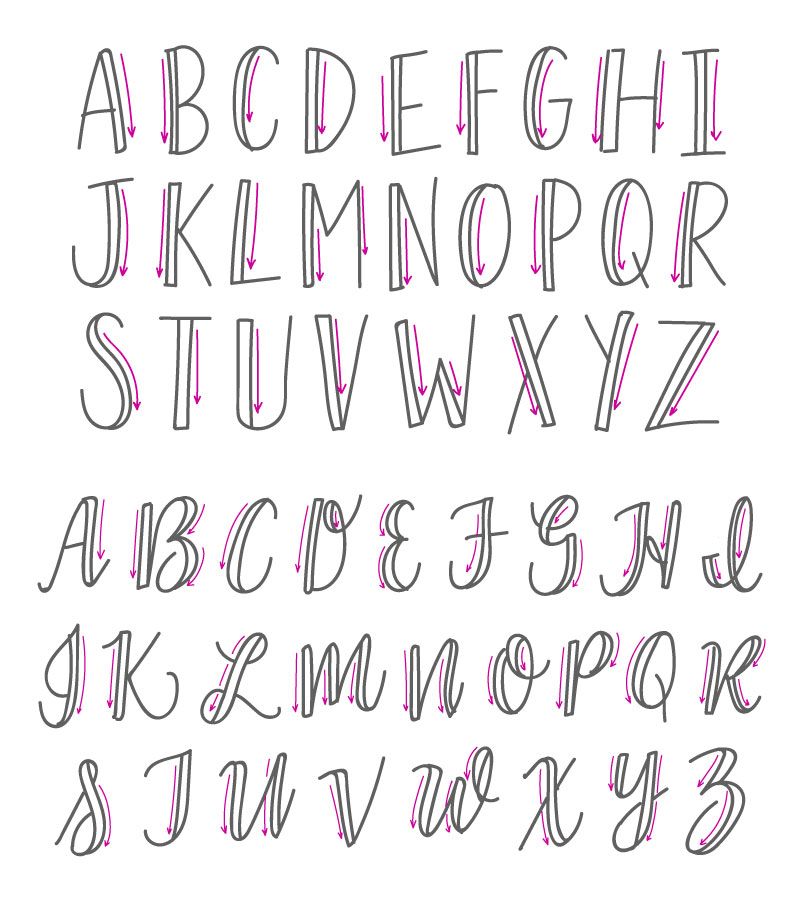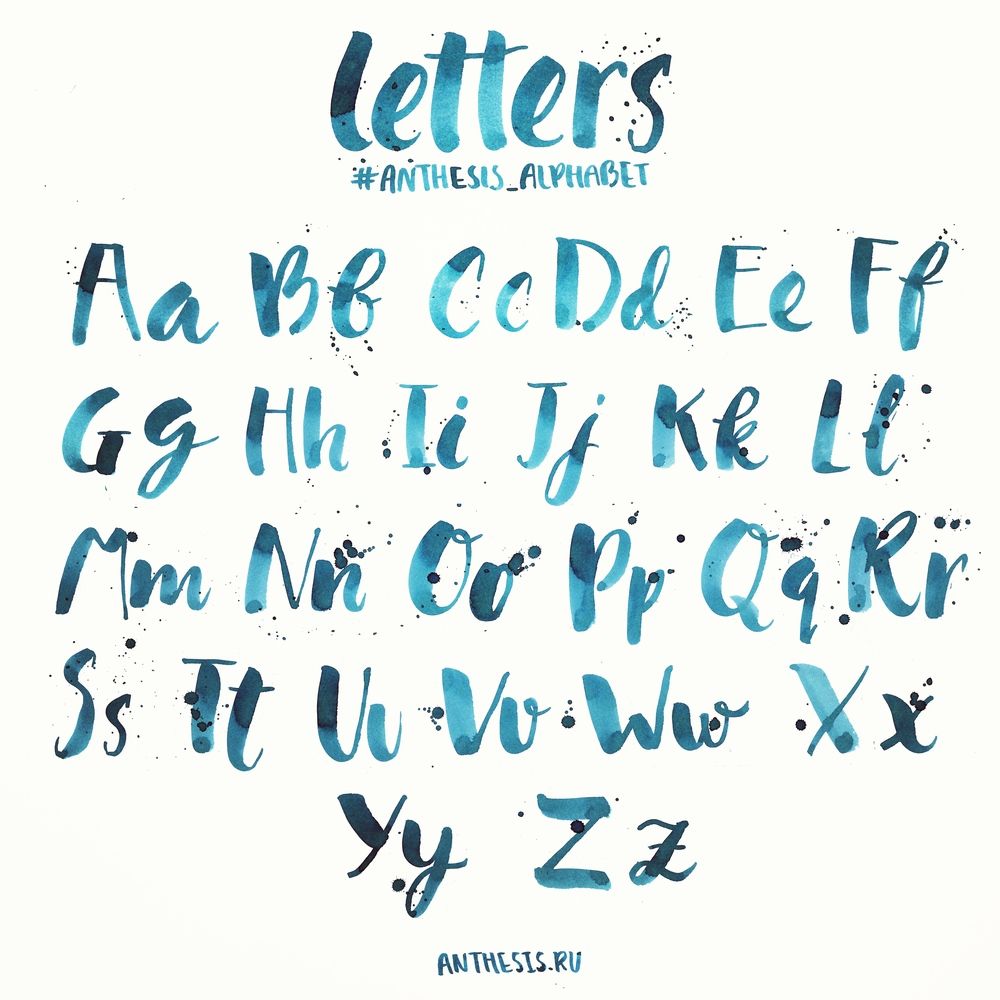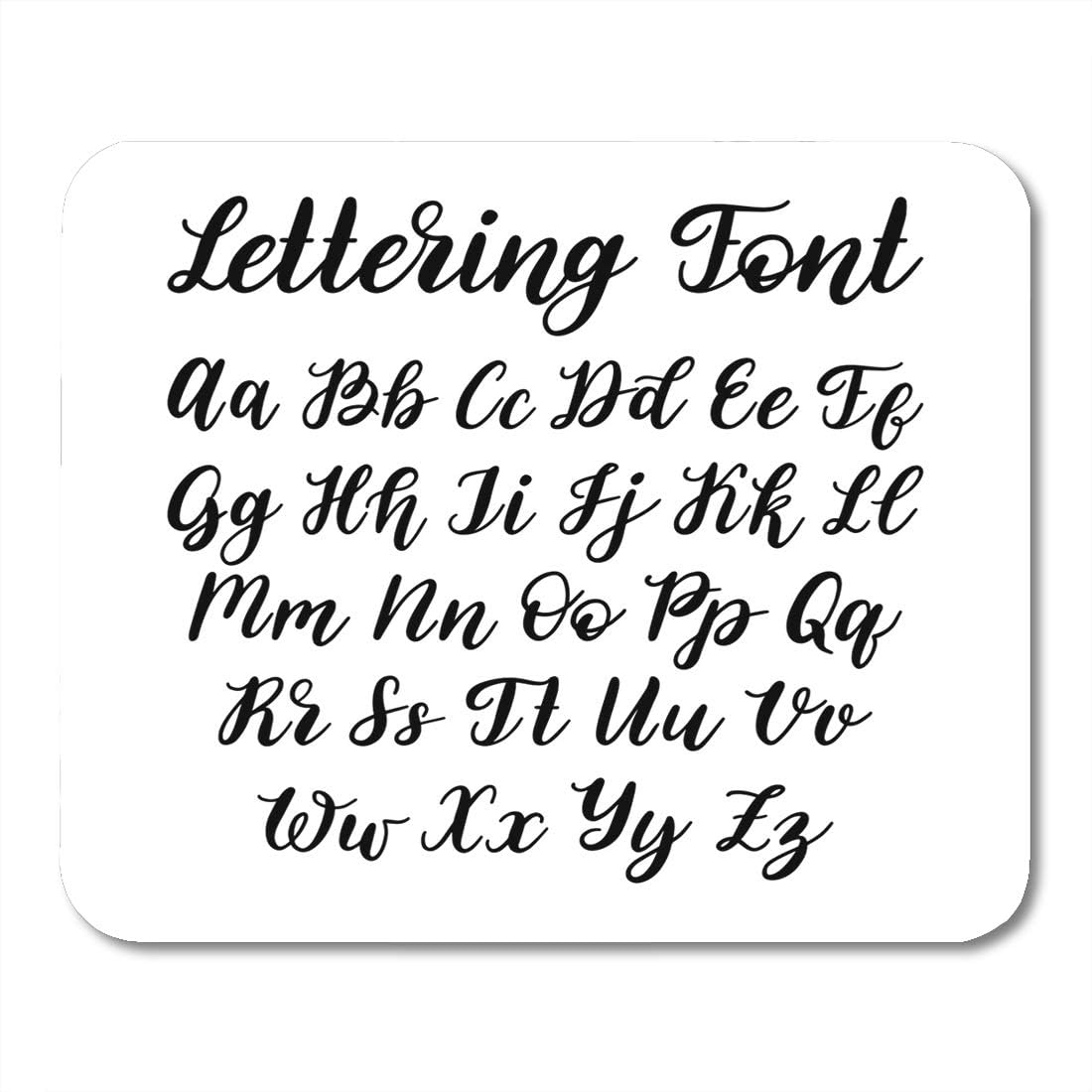
Леттеринг — отличный способ «одушевить» ваш проект
Большая обзорная статья от дизайнера Александра Кочеванова, который подробно рассмотрел отличия шрифта, леттеринга и каллиграфии, а также способы и особенности применения каждого в проекте.
Смотря фильмы про будущее мы очень часто видим такую картину: одинаковые, словно клонированные, люди в одинаковой одежде. Их окружают одинаковые автомобили и дома на одинаковых улицах. Люди трудятся на благо огромных корпораций, осуществляя монотонные телодвижения перед компьютерами или перекладывая бумажки с места на место.
Все вокруг бездушное и унылое, преобладают голубые, серые и белые оттенки с небольшими вставками ярких цветов для ключевых героев фильма. Наверняка это сделано для придания большей ироничности сюжету фильма. И, конечно, я отдаю себе отчет в том, что это утопия и в обозримом будущем такого не случится. Но одно я знаю точно. Я и подавляющее большинство людей никогда бы не захотели жить в таком мире.
Но некоторые отголоски такой картины можно наблюдать и сегодня. При решении многих задач мы используем шаблоны: фреймворки, конструкторы, шаблонные сайты, интерфейсы, логотипы, предметы быта и прочее. Все направлено на удешевление производства и быстрый выход на рынок. Выгода с экономической точки зрения, конечно, очевидна. Но со стороны потребителя становится скучно и однообразно.
Существует много способов «одушевить» продукт: придумать зверюшку-символ, использовать образы людей, фотографии, иллюстрации. Я расскажу вам о леттеринге. Осторожно — много картинок!
В первую очередь, нужно различать 3 понятия.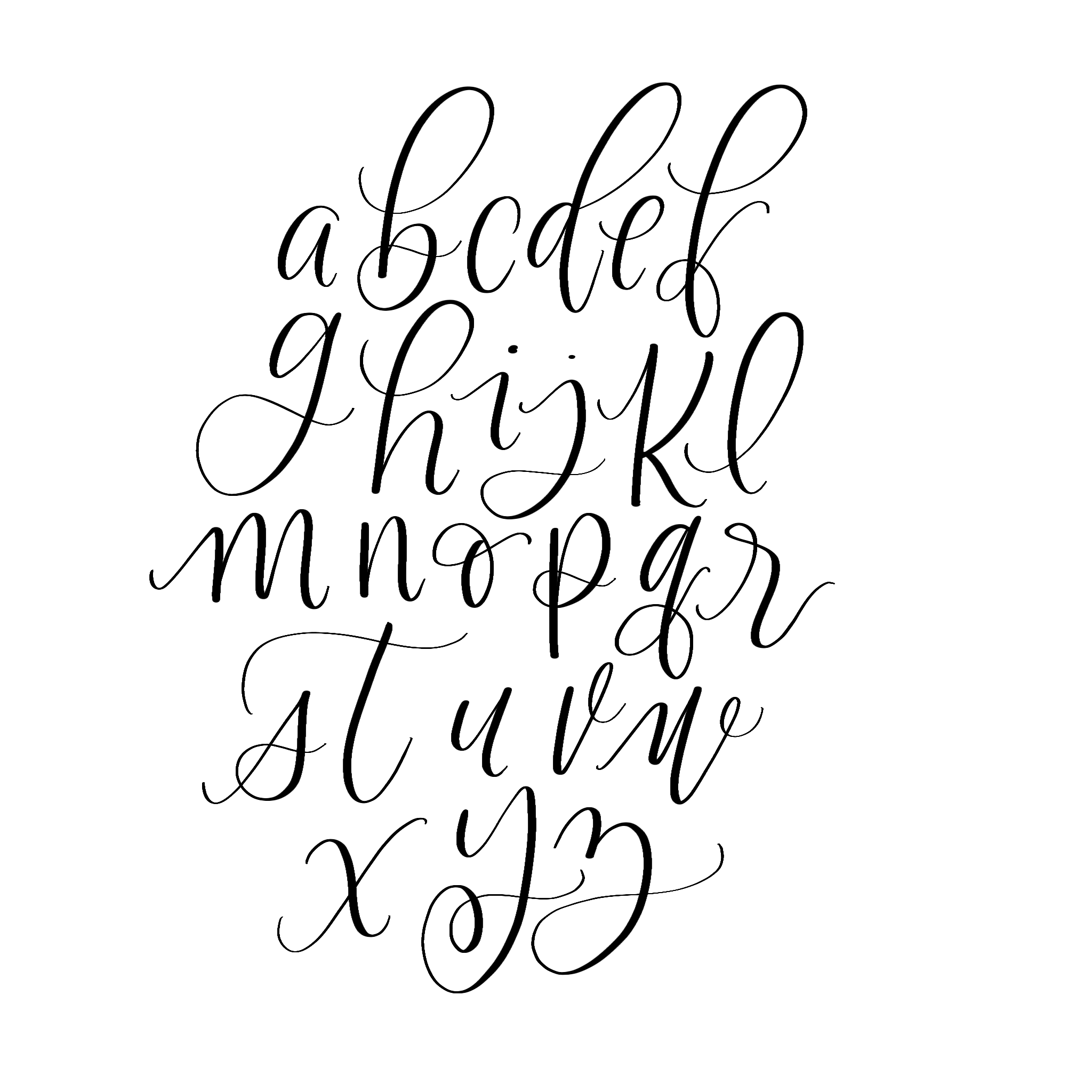
Шрифт — набор из символов, которые могут использоваться в любом порядке и служат для написания слов, предложений и текстов большого объема.
Леттеринг — уникальное рисование слова или словосочетания, изредка целых фраз, которое составляет единую композицию и предназначенное для конкретной ситуации.
Каллиграфия (с греческого «красивый почерк») это тоже ручная надпись, но, в отличие от леттеринга, все буквы должны придерживаться единого стиля и образовывать читабельный блок текста. Каллиграфией можно писать большие тексты, например грамоты или письма.
И леттеринг и каллиграфия создаются долгим и кропотливым трудом мастера. Но только леттеринг основан на вырисовывании букв и поиске уникального неповторимого сочетания символов, в то время как каллиграфия — это огромное количество повторений одних и тех же букв с целью написания текста в едином стиле.
Немного истории
Сначала были наскальные рисунки, в Древнем Египте были различные символы, потом появились буквы и цифры — человечество научилось писать.
Ручное письмо было повсюду: личные письма, книги, приказы и законы. Все писалось с помощью перьев: так зародилась каллиграфия. С появлением печатных машин и, вслед за ними, компьютеров начали появляться шрифты. Это очень способствовало повышению уровня образования. Книги стали более доступны, даже простые крестьяне и рабочие, со временем, научились читать и писать. Тем временем, леттеринг с появлением письменности развивался постоянно. Нужно было как-то оформлять вывески, афиши, этикетки, обложки.
Приятная тенденция
Я считаю, что сегодня, если и не пик, то рост использования леттеринга точно. Сегодня многие компании стараются сделать свои бренды «живыми». Появляются не магазины и бутики, а лавки: творческие, мясные, булочные, швейные и прочие. Это, в некоторой степени, возврат к прошлому. Оформляются логотипы таких заведений именно леттерингом. Внутри очень часто можно встретить меловые стены с меню или просто с изображением продукции.
Потому что, это создает атмосферу тепла и уюта. И мне это нравится.
Ровно год назад в новогодние дни на первом канале транслировались крутые вставки созданные с помощью доски и мела.
Процесс создания можно посмотреть на сайте Игоря Мустаева. Очень интересно.
Мировые СМИ и такие печатные издания как Time, Esquire, Vogue, Forbes по полной используют этот инструмент.
Огромное количество логотипов создано с помощью леттеринга. Конечно, Вы можете сказать, что их намного меньше чем классических логотипов, набранных каким-нибудь шрифтом. И вы будете абсолютно правы. Многие хотят выглядеть серьезно и в некоторых случаях это даже необходимо. Но очень многому количеству компаний был бы к месту именно «ручной» логотип.
И не подумайте, что я призываю все бросить и везде подряд использовать рисованные буквы. Я просто прошу обратить на это внимание, как на прием воздействия на потребителя. Но если, все-таки леттеринг вам интересен, листайте дальше.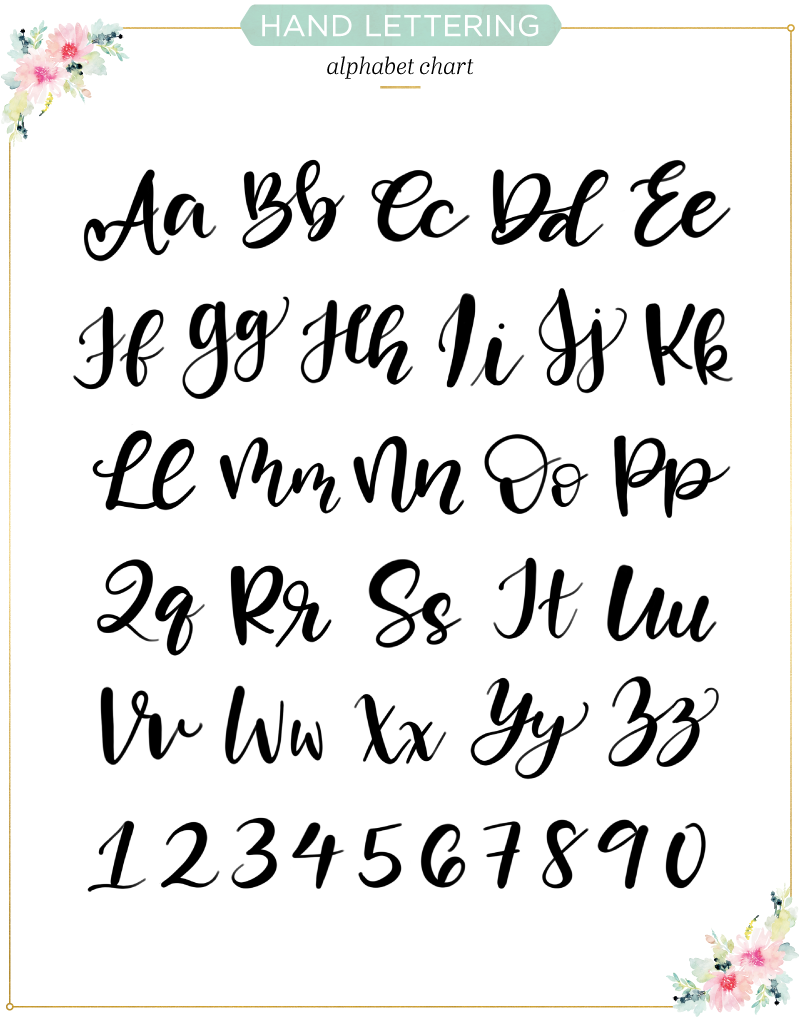
Кто поможет с леттерингом?
Некоторое время назад, заинтересовавшись леттерингом, мне потребовалось место, где бы я мог складировать все найденное интересное. Я кидал все в этот паблик.
Мне попадалось много “забугорных” мастеров, но я решил сконцентрироваться на русскоязычных каллиграфах, леттерерах, дизайнерах и иллюстраторах. Находятся они, в большинстве своем, в России и на постсоветском пространстве. Попадались люди разной квалификации. Ниже я приведу список всех 226 человек. Но в первую очередь 30 тех, кто на мой взгляд круче.
Очевидно, кто-то мог не попасться мне на глаза, если есть дополнения, смело пишите в комментах.
1. Александр Стэн
2. Андрей Мартынов
3. Андрей Хобб
4. Виктор Пушкарёв
5. Виктор Севрюков
6. Виктория и Виталина Лопухины
7. Владимир Егошин
8. Гоша Бондарев
9. Даша Левчук
10. Дмитрий Ткачёв
11. Евгения Пестова
12.
Иван TAKNADO Fans
13. Игорь Ветошкин
14. Игорь Мустаев
15. Катерина Рахманова
16. Кирилл Плотников
17. Макс Брис
18. Мария Скопина
19. Михаил Левченко
20. Миша Новожилов
21. Назим Исмагилов
22. Никита Райзвих
23. Ольга Васик
24. Родион Илюхин
25. Сергей Шапиро
26. Стас Курап
27. Эрик Мусин
28. Юлия Тасито
29. Evgeny Tkhorzhevsky
30. Kirill Richert Mihailovich
Есть еще один мастер, которого я сначала вообще не хотел включать в этот список, но потом решил упомянуть. Потому, что его работы, как правило, носят декоративный характер, и не имеют практического применения. Его работы — это искусство, смотря на которые можно только получать эстетическое удовольствие. Речь идет о Покрасе Лампасе.
Источник: habrahabr.ru
- #каллиграфия
- #леттеринг
- #типографика
- 0
10 алфавитов для написания букв от руки, с которыми вам нужно попрактиковаться Прочитайте мое раскрытие здесь.
10 Рукописные листы по написанию алфавитов. Используйте эти рабочие листы с вашим Tombow Fudenosuke и разработайте свой собственный уникальный стиль письма!
Хотите улучшить свой почерк или придать ему художественный вкус? Эти бесплатные рабочие листы для практики письма от руки помогут вам научиться рисовать буквы, практиковать штрихи и создавать алфавит.
Один из лучших способов попрактиковаться в написании букв и выработать свой собственный уникальный стиль — использовать разные шрифты.
Практикуя разные способы рисования одной и той же буквы, вы начнете замечать, какие стили вам нравятся, и, прежде чем вы это узнаете, вы начнете видеть, как ваш собственный стиль воплощается в жизнь.
Прокрутите вниз, чтобы найти 10 алфавитов, написанных от руки, и почему бы не делать по одному алфавиту в день в течение 10 дней!?
Рабочие листы с алфавитом от руки всегда популярны, и эти рабочие листы охватывают как прописные, так и строчные буквы алфавита.
Со всеми этими практическими таблицами вы научитесь писать письма в кратчайшие сроки.
Помните, практика — единственный способ добиться совершенства. Поэтому убедитесь, что каждый день немного тренируетесь писать от руки.
Как начать писать?
Интернет полон написанных от руки цитат и изображений, которые могут вас вдохновить. Вы можете найти вдохновение в Instagram, выполнив поиск #handletred и прокрутив ленту вниз (часами, если вы чем-то похожи на меня!) или проверить Pinterest и создать новую доску для вдохновения от руки.
Когда вам надоест прокручивать ленту, вы можете начать изучать стили, которые вам нравятся, и отмечать, что вам не нравится.
Когда вы будете готовы попробовать написать надпись, все, что вам нужно, это обычный карандаш или какой-либо маркер (маркер Crayola отлично подойдет) и лист бумаги!
Правильные расходные материалы облегчат написание рукописных букв, но вам не нужно сразу же идти и тратить целое состояние на ручки и карандаши или насадки для кистей.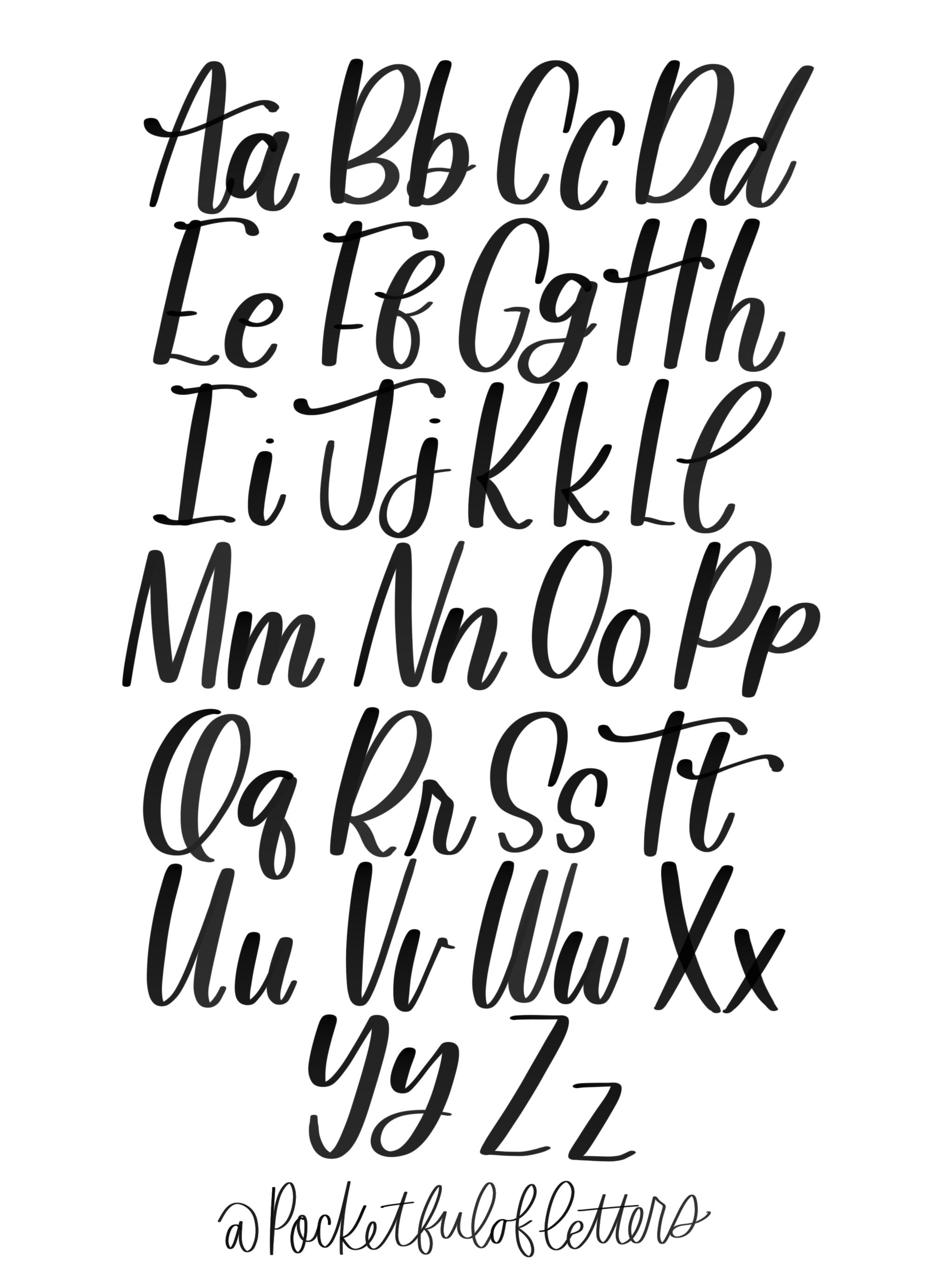
Возьмите маленькое слово или просто букву по вашему выбору и нарисуйте ее всеми возможными способами. Заполните хотя бы целую страницу разными вариантами буквы или слова.
Просто начните играть с буквами и получайте удовольствие. Не беспокойтесь о том, что это хорошо или красиво, потому что нет ничего неправильного или правильного, когда дело доходит до надписей. Это просто о том, чтобы попробовать что-то новое и посмотреть, как далеко вы можете продвинуть свои буквы, и это делает это таким увлекательным!
Как научиться писать от руки?
Есть много книг и видео, которые помогут вам научиться писать от руки, но вы не научитесь, пока не начнете прикладывать ручку к бумаге.
Перед тем, как вы погрузитесь в буквенное обозначение, важно знать наиболее часто используемые термины, чтобы в следующий раз вы могли называть «маленькую штучку на конце строчной буквы» ее именем — терминалом. . Зная эти термины, вы сможете говорить с кем угодно на эту тему.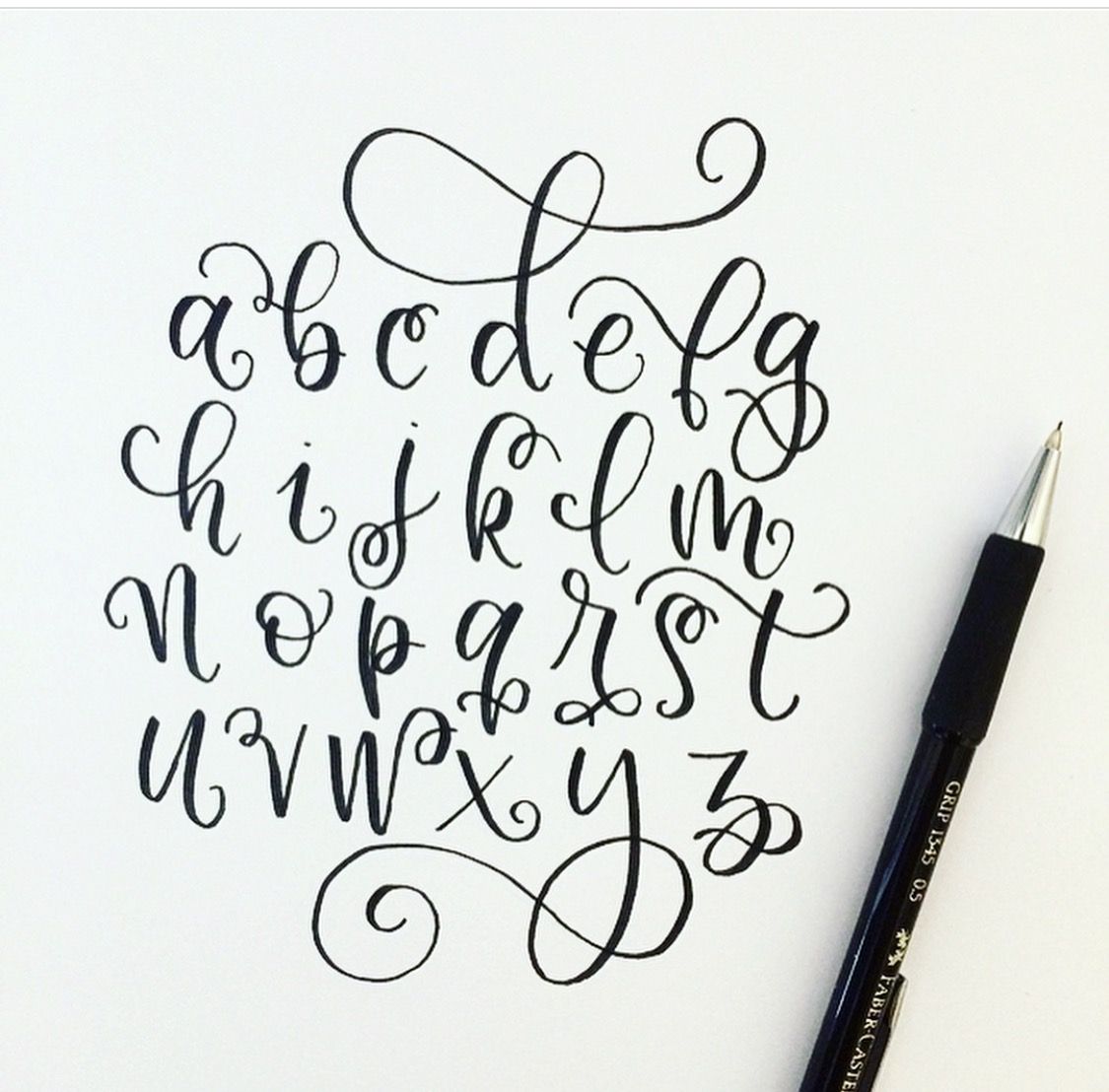
Какие ручки лучше всего подходят для письма от руки?
Чтобы начать рисовать от руки, вам не нужны какие-то причудливые и дорогие ручки-кисти. Если у вас дома есть пара маркеров Crayola, все готово! У маркера Crayola нет наконечника-кисти, но он по-прежнему остается одной из самых популярных ручек для надписей.
Если вы все же хотите приобрести качественные ручки-кисти, вот мои рекомендации:
- Ручка-кисть Tombow Dual – Эти ручки-кисти имеют две стороны. С одной стороны вы найдете гибкий кончик кисти, а с другой — твердый тонкий кончик, который можно использовать для добавления мелких деталей в вашу работу или внесения незначительных исправлений.
- Tombow Fudenosuke . Эта ручка-кисть имеет маленький наконечник, с которым гораздо легче учиться, чем с ручками-кистями с большим наконечником. Если вы новичок в написании букв от руки, то я бы порекомендовал вам приобрести эту ручку.
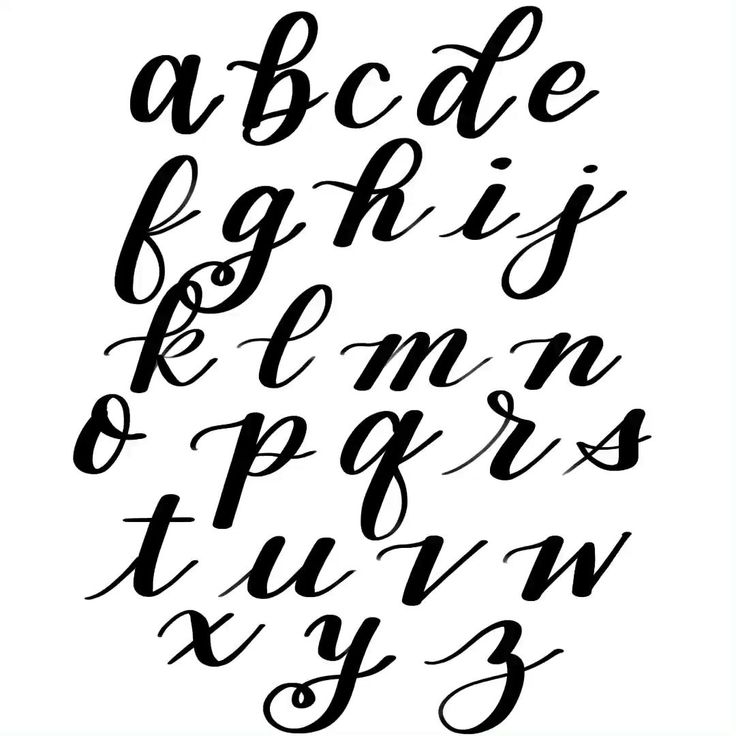
- Ручка-кисть Pentel Arts Pocket . Эта ручка-кисть довольно экономична и доступна по цене. Ручка многоразовая, поэтому, когда щетина изнашивается, вы просто заменяете ее вместо того, чтобы покупать полностью новую ручку, что делает ее более долговечной, чем другие ручки-кисти.
В чем разница между рукописным шрифтом и каллиграфией?
В двух словах, каллиграфы пишут буквы, леттеры рисуют их, а типограф разрабатывает форму шрифта, чтобы сделать написанное слово более читаемым.
Другим большим отличием являются инструменты и методы, используемые для создания рукописных надписей или каллиграфии.
Большинство людей думают только о «стиле письма», говоря о каллиграфии, но существует огромное количество стилей, которые можно написать. Хотя нетренированному глазу может быть трудно заметить разницу между рукописным шрифтом и каллиграфией, вы должны помнить, что основное различие заключается в том, как он создается.
Это самое простое объяснение разницы между ними.
Тем не менее, давайте углубимся в это, чтобы вы могли получить полное и четкое представление о том, что такое рукописный шрифт и каллиграфия 9.0005
Узнайте больше о разнице между рукописным шрифтом и каллиграфией здесь.
Что означает надпись от руки?
Надпись от руки — это, по сути, рисование букв с использованием необходимого количества штрихов вместо того, чтобы печатать их с помощью клавиатуры.
Это отличается от каллиграфии, где мы используем основные штрихи для формирования букв и слов. Вы также часто имеете больший контроль над буквами с помощью рукописного ввода, а не каллиграфии. По этой причине ручная надпись может быть отличной альтернативой для проектов, которые слишком велики для каллиграфии, таких как большие классные доски и другие вывески.
Как улучшить рукописный шрифт?
Если вы хотите улучшить свои навыки письма, вам нужно ежедневно практиковаться.
Но в некоторые дни может быть трудно сохранять мотивацию и продолжать тренироваться, когда вам не хочется.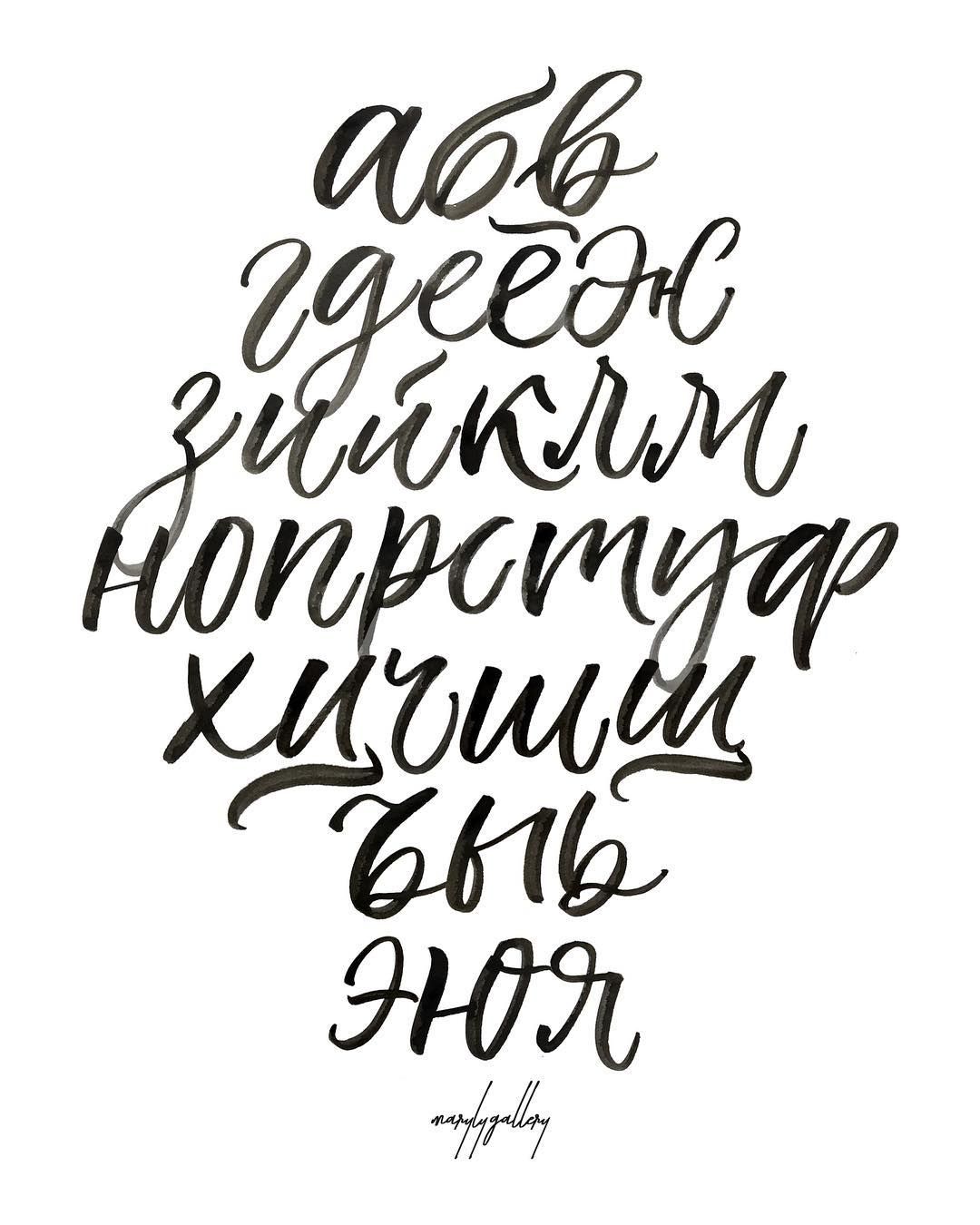
Вот когда челлендж поможет вам сосредоточиться на своих целях.
Если вам нужна мотивация для ежедневной практики, вы можете бесплатно принять участие в моем конкурсе Year of Lettering Challenge. Или, если вам нужна дополнительная поддержка в процессе работы, вы можете присоединиться к моему конкурсу «30 дней работы с маленькой кистью», чтобы получать ежедневные листы с практическими рекомендациями и советы.
Для этих печатных рабочих листов вам понадобятся:
- Практика письма от руки (ниже) 900 83
- Ручка Tombow Fudenosuke
- Бумага для маркеров (дополнительно)
Загрузите печатные формы в формате PDF ниже, распечатайте их на бумаге, подходящей для кистей (например, HP Premium Choice Laser Jet Paper), и начните писать надписи!
Вы можете рисовать прямо поверх него или взять лист кальки и провести по нему столько раз, сколько захотите.
Советы по рисованию букв
Чтобы получить максимальную отдачу от практики, вот несколько советов, которые помогут сразу улучшить качество письма:
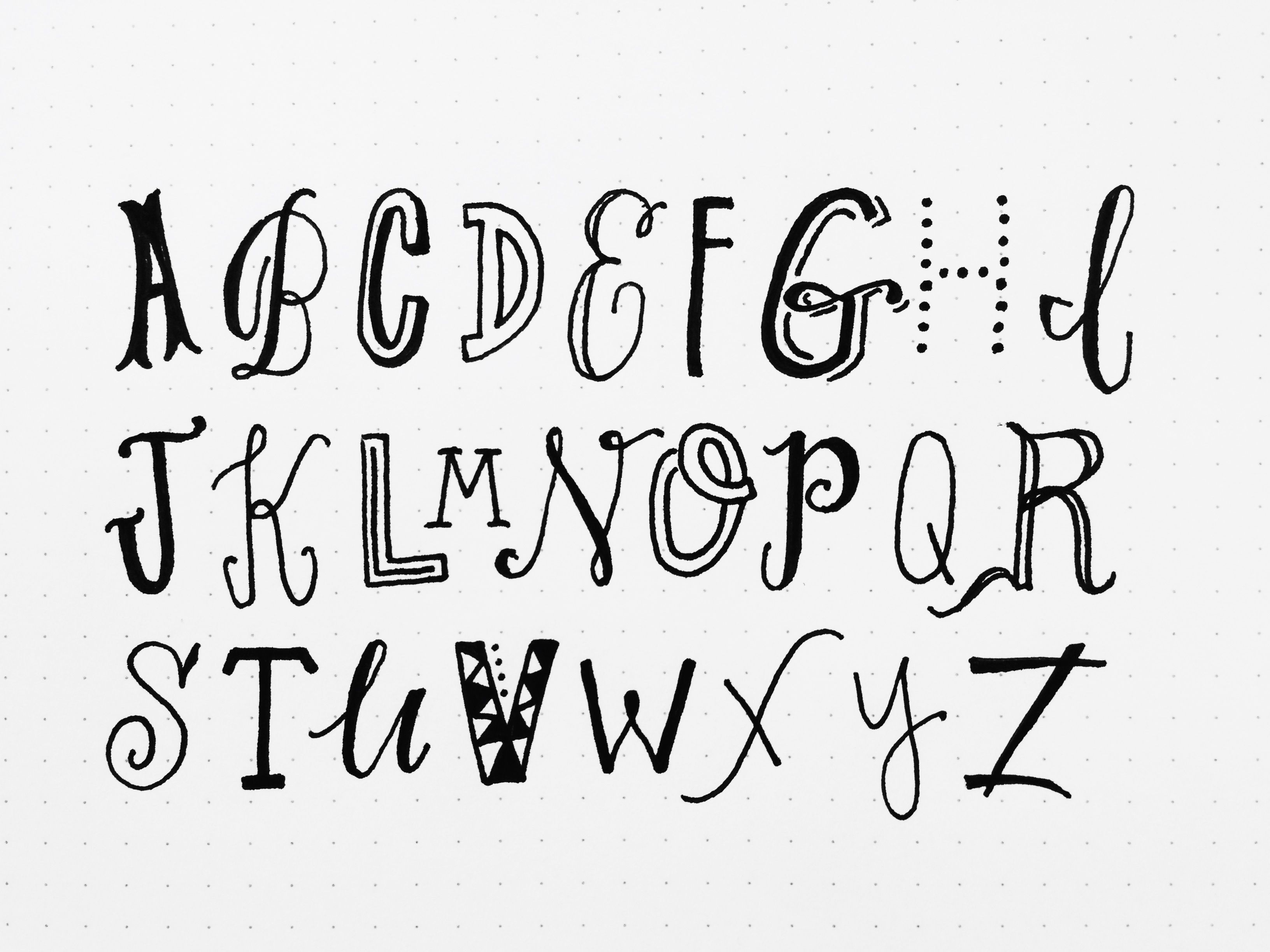
Узнайте больше советов по написанию букв здесь!
Загрузить листы с упражнениями по написанию букв алфавита
Готовы загрузить листы с упражнениями по написанию букв?!
Fonts Matter
Выбор правильного шрифта кажется тривиальным решением, но одна крупная ошибка может изменить все определение текста.
Шрифты имеют разные особенности, которые могут вызывать доверие или недоверие и даже облегчать работу.
Хотя большинство знает о неправильных шрифтах для вашего резюме или веб-сайтов, выбор шрифта в дизайне все еще находится в стадии разработки; к сожалению, для некоторых это привело их в небезопасные воды. Просто посмотрите ниже, чтобы найти пример, который доказывает, что шрифты действительно имеют значение.
Ищете дополнительные ресурсы по рукописным надписям? Ознакомьтесь также с этими сообщениями:
- Лучшие подарки для любителей ручного письма в 2018 году
- 17 талантливых дизайнеров рукописного письма будут вдохновлены
- Узнайте, как писать буквы с помощью этих рабочих листов для письма от руки
- 11 лучших бесплатных листов для практики письма от руки
Условия использования: Эти печатные формы предназначены только для личного использования и © 2020 Awesome Alice.
Вы не можете изменять их или распространять с целью получения денежной выгоды. Вы можете поделиться этими бесплатными рабочими листами, только используя ссылку на этот оригинальный пост в блоге на awesomealice.com. Спасибо!
Надеюсь, вам понравятся тренировочные листы алфавита от руки! Если вам нужно еще больше тренировочных листов, вы можете найти еще 10 БЕСПЛАТНЫХ тренировочных листов для начинающих здесь!
Счастливого письма!
Продолжайте читать…
Виктория | Awesome Alice
Виктория любит все, что касается рукописного письма, ваш новый рукописный шрифт, мистер Мияги, и основатель AwesomeAlice.com, сайта для занятых женщин, желающих научиться писать от руки.
С помощью своего популярного набора «Надпись от руки» и курса «Просто начни леттеринг» она делает обучение рисованию от руки легким и увлекательным, чтобы занятые женщины во всем мире могли научиться уверенно создавать красивые надписи, которые принесут больше смысла и радости в их жизнь! Чтобы узнать о книгах и программах Виктории, посетите: shop.
awesomealice.com
12 страниц с буквами винтажного алфавита!
Сегодня у нас есть прекрасная коллекция старинных страниц с буквами алфавита. Вот некоторые страницы, которые были у меня в блоге в течение многих лет, но они были спрятаны в архивах, поэтому, вероятно, вы не видели большинство из них раньше, а если и видели, то, вероятно, очень давно. ! В любом случае, это все любимые страницы ABC, показывающие Алфавит всевозможными шрифтами. Их можно использовать в самых разных проектах, но я думаю, что они станут отличным фоном для коллажей или смешанной техники!
Винтажные страницы с алфавитом
Такие красивые алфавиты, как вы думаете? Вот великолепная типографская страница из старинной книги Circa 1920. На этой странице есть три стиля рукописного письма — итальянский MS, Half Uncial Treeter и Cathedral Door. Их подарила мне дорогая подруга Мэг! Она великодушно отсканировала их и предложила мне поделиться ими со всеми вами. Мне нравится, насколько четкими и четкими выглядят эти буквы в стиле каллиграфии.
Спасибо Мэг!
Вот еще одна великолепная типографская страница из старого Circa 19.Книга с 20 надписями. В этом примере также есть три разных каллиграфических шрифта — English Text Capitals, Dürer Blackletter Capitals и Uncial Capitals. Это, конечно, заглавные буквы. Такие красивые алфавиты вы не находите?
В этом примере также отсканировано из старинной книги три разных каллиграфических шрифта — English Text, Dürer Blackletter и Flourished Blackletter. Это строчные буквы. Мне нравится, как мило выглядят эти буквы. Они могли бы стать забавным фоном для мультимедийного проекта!
Образцы рукописного письма Old Alphabet
Вот образец из книги по рекламе начала 1900-х годов. Эта книга наполнена всевозможными удивительными вещами, включая множество примеров красивой типографики, подобной той, что вы видите выше. Этот называется Эксцентричный египтянин. Это немного эксцентрично с его волнистыми линиями. Запятые мне кажутся усами. Как весело!
Этот замечательный образец винтажной типографики взят из книги по чистописанию 1870-х годов.
Это действительно великолепная книга. Надпись выше в книге называлась Spured Alphabet. Мне просто понравилась уникальная форма этих букв, и так приятно иметь их версии в верхнем и нижнем регистре! Было бы интересно научиться рисовать этот шрифт! Выше приведен образец шрифта Blackletter. Интересно, что это один из старейших шрифтов, датируемый 1400-ми годами. Эти ранние шрифты напоминали рукописную каллиграфию. Один из них — древнеанглийский, а другой — немецкий текст. Убедитесь, что вы увеличиваете масштаб этого! В комплекте маленькие декоративные безделушки, которые я люблю!
Винтажные страницы с надписями
Вот еще одна красивая страница с надписями. У этого есть несколько забавных цитат. Мне нравится, что он показывает положение, в котором вы должны держать перо. Обратите внимание на «Keep Cool» в нижнем углу. Это заставляет меня думать о «Сохраняйте спокойствие…» Отличный совет!
Это еще одна из прекрасных страниц с надписями. Теперь, когда я смотрю на это, я думаю, что это может быть мой любимый еще! Он показывает вам, как создать несколько строчных букв с перекрестной штриховкой.